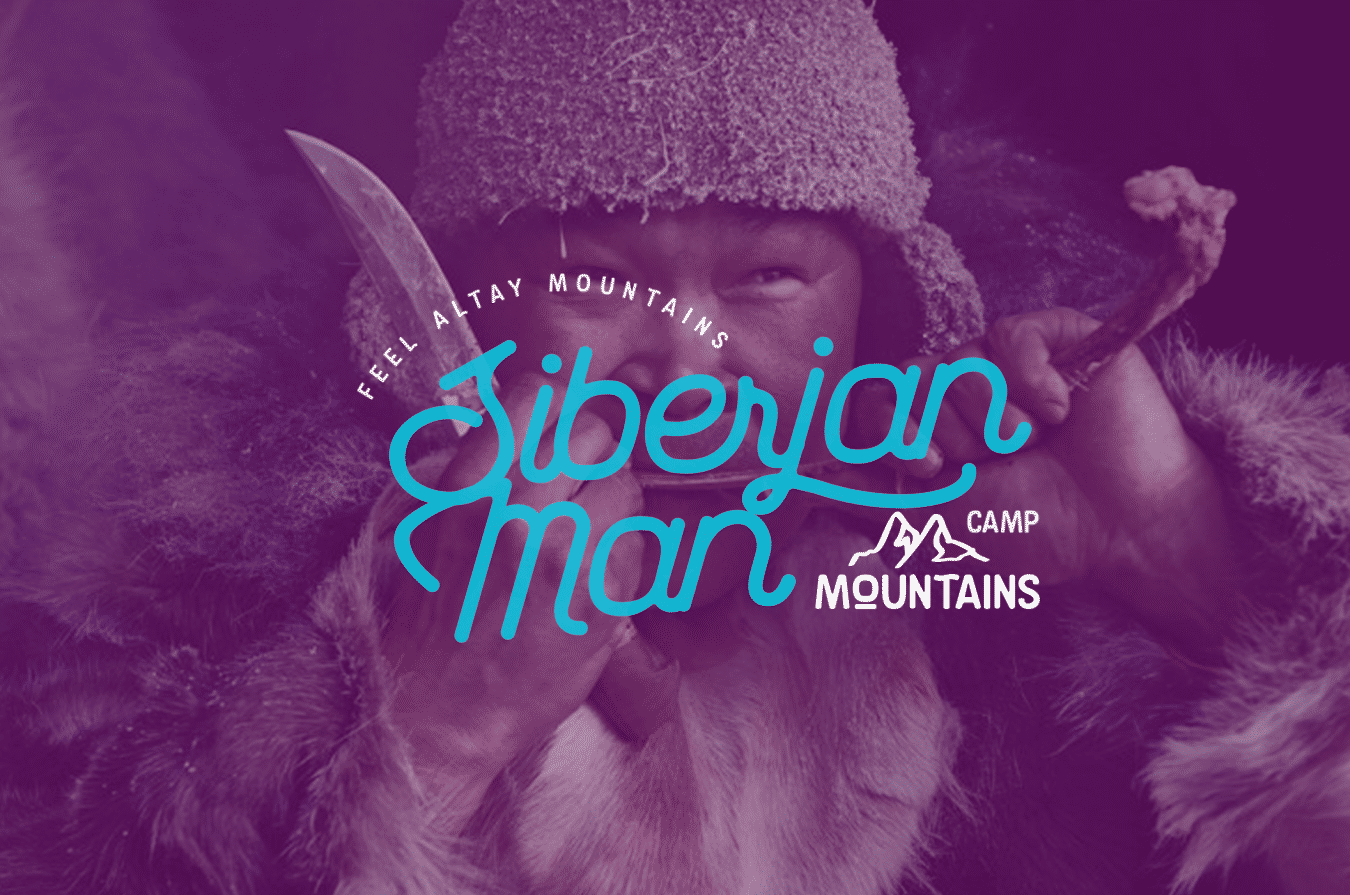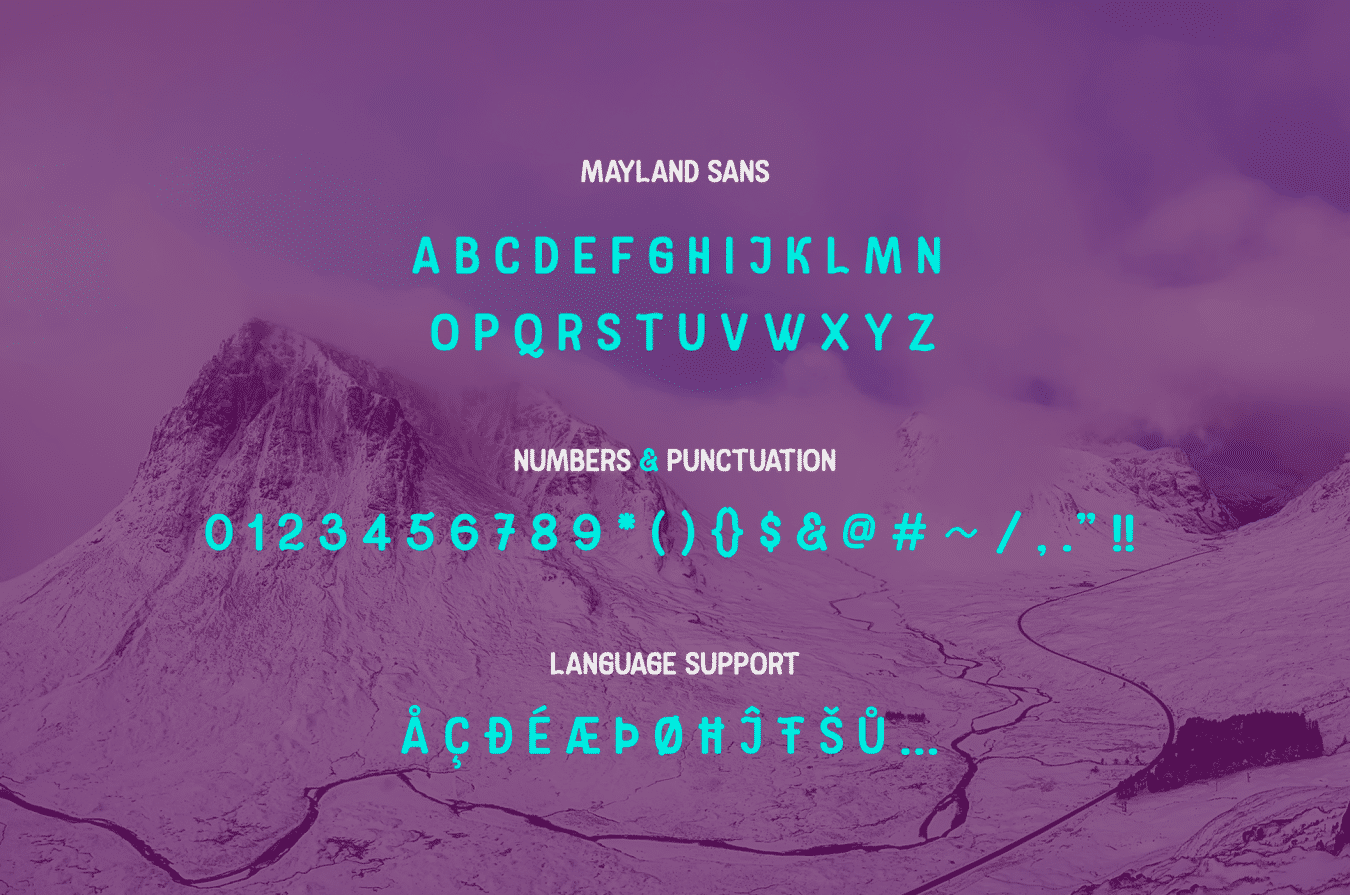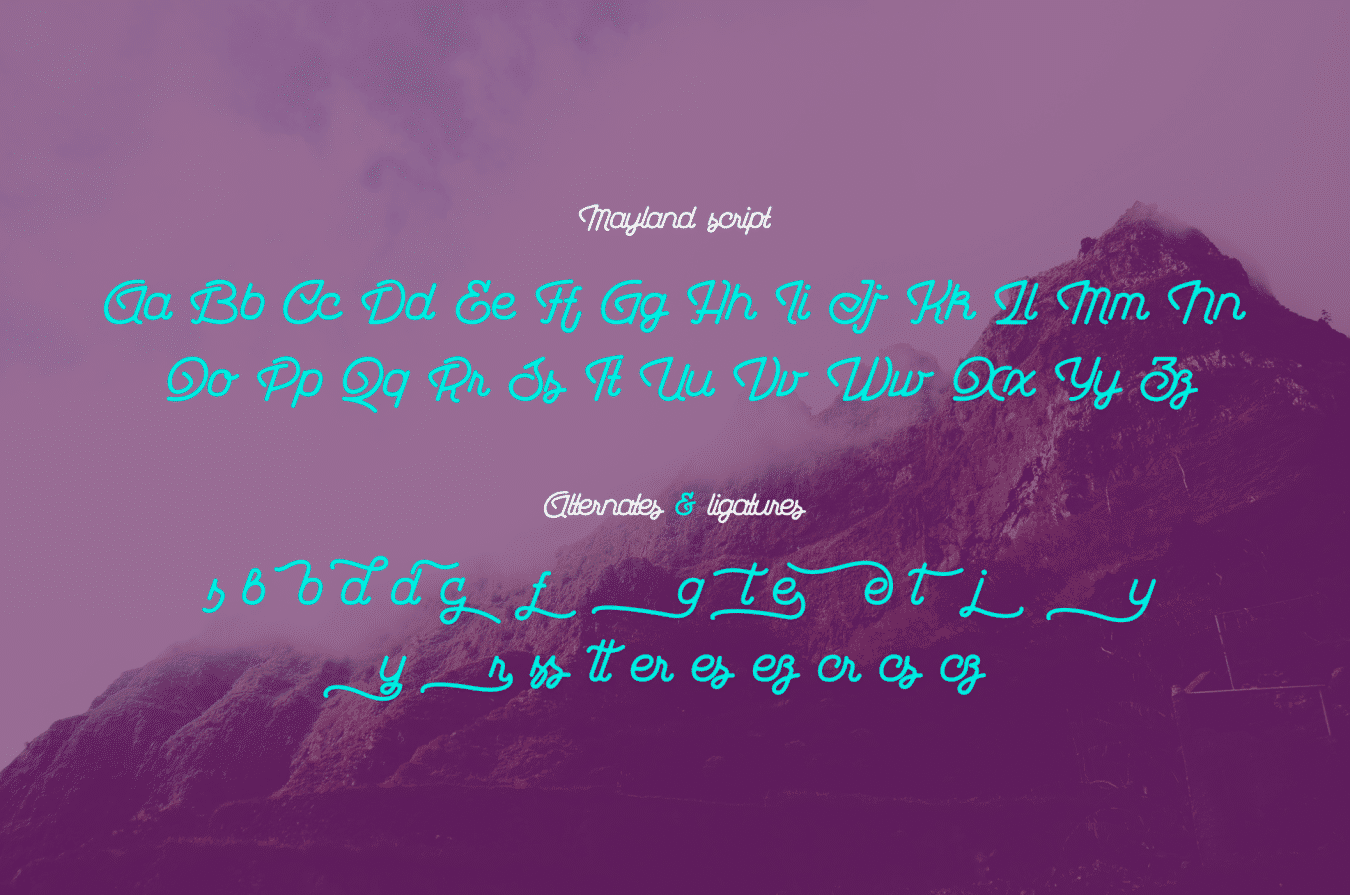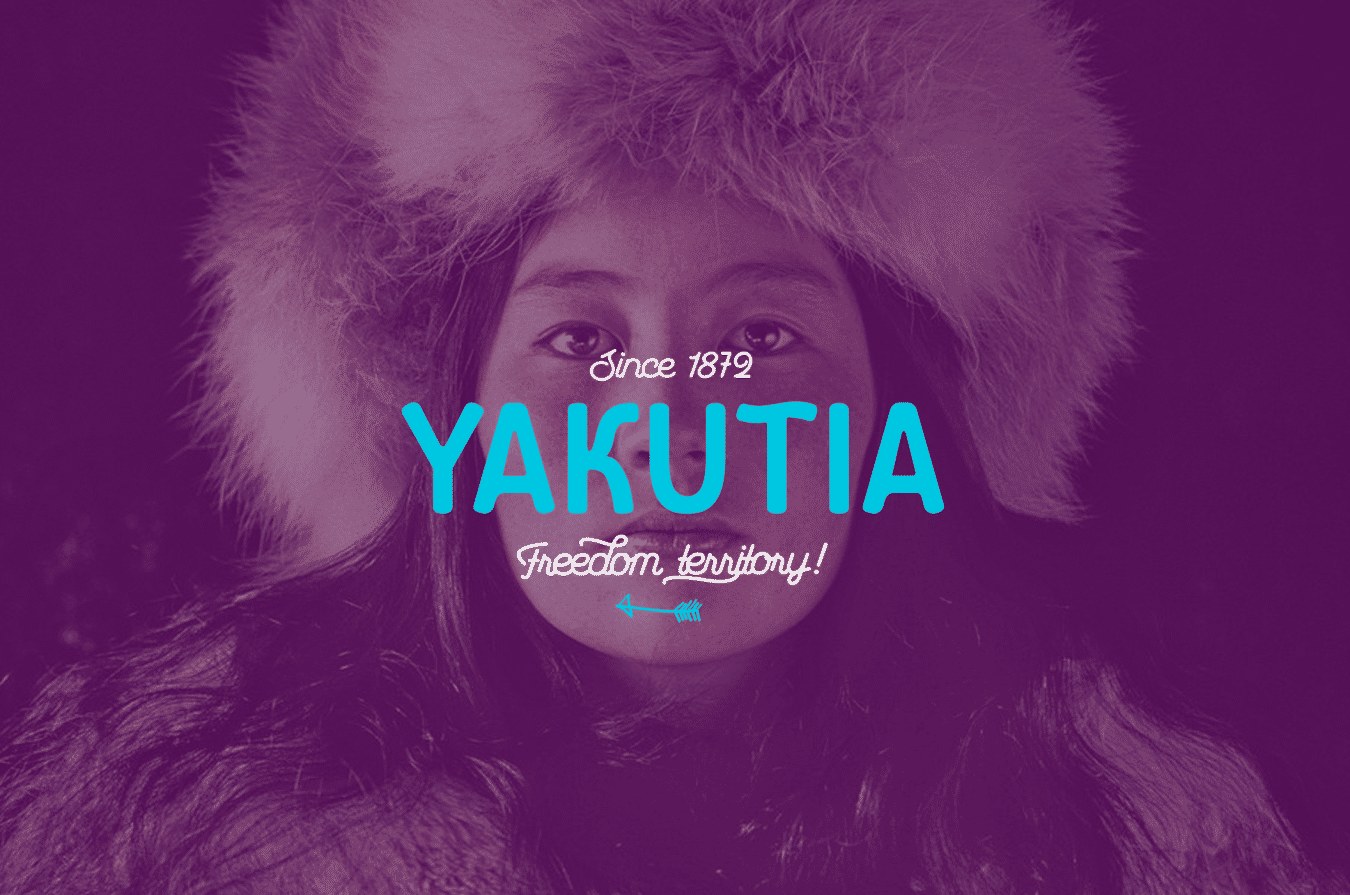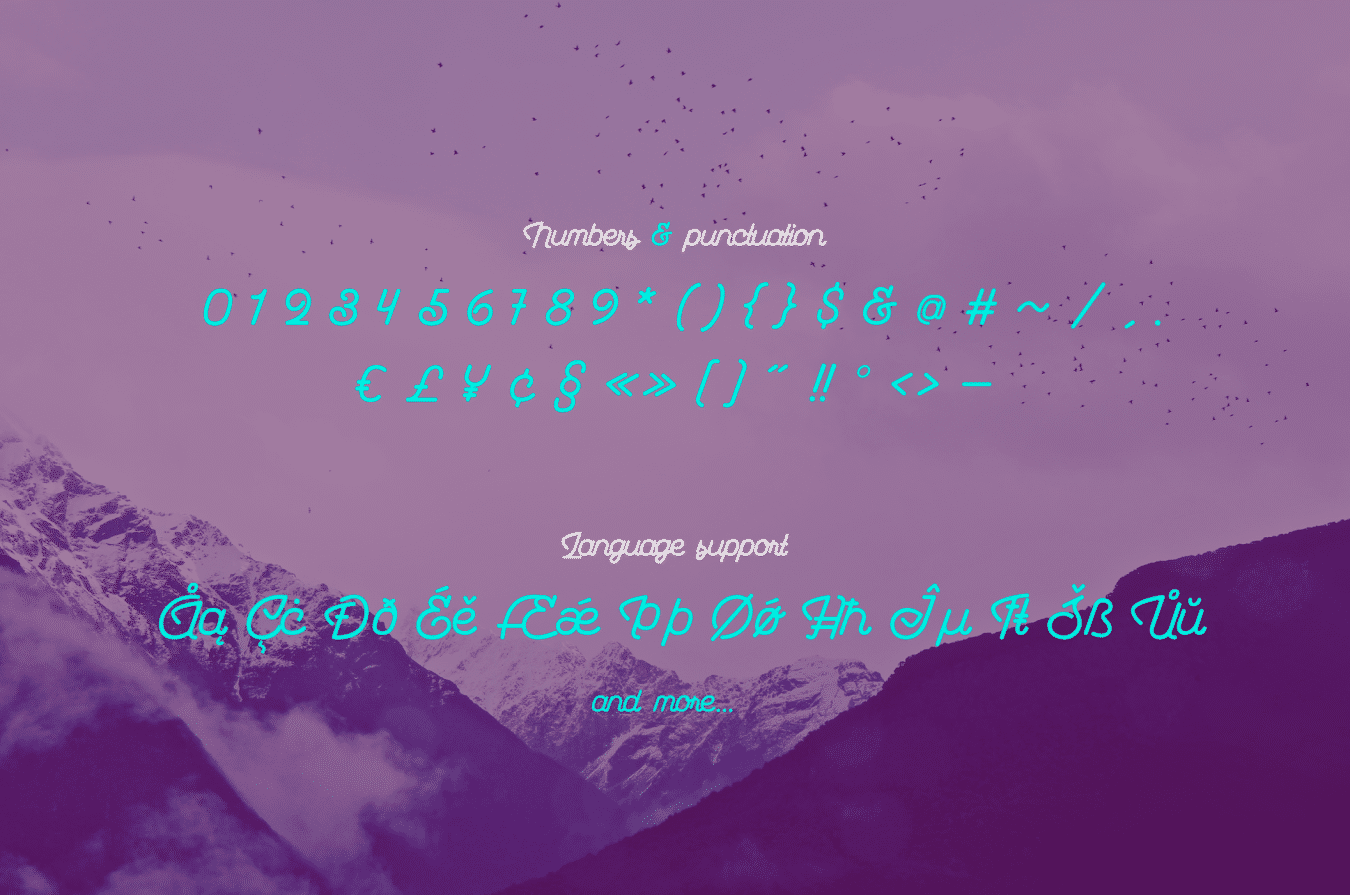
来自西伯利亚的Mayland Script和Mayland Sans with love。,Mayland Typeface Duo
Mayland Script and Mayland Sans from Siberia with love., Mayland Typeface Duo
Mayland Typeface Duo是一款手工制作的剧本和无字体字体。 Mayland将适用于各种不同的创意作品,它具有漂亮的圆角和线条,可用于友好的图形。此OTF和TTF字体包含替代字形。